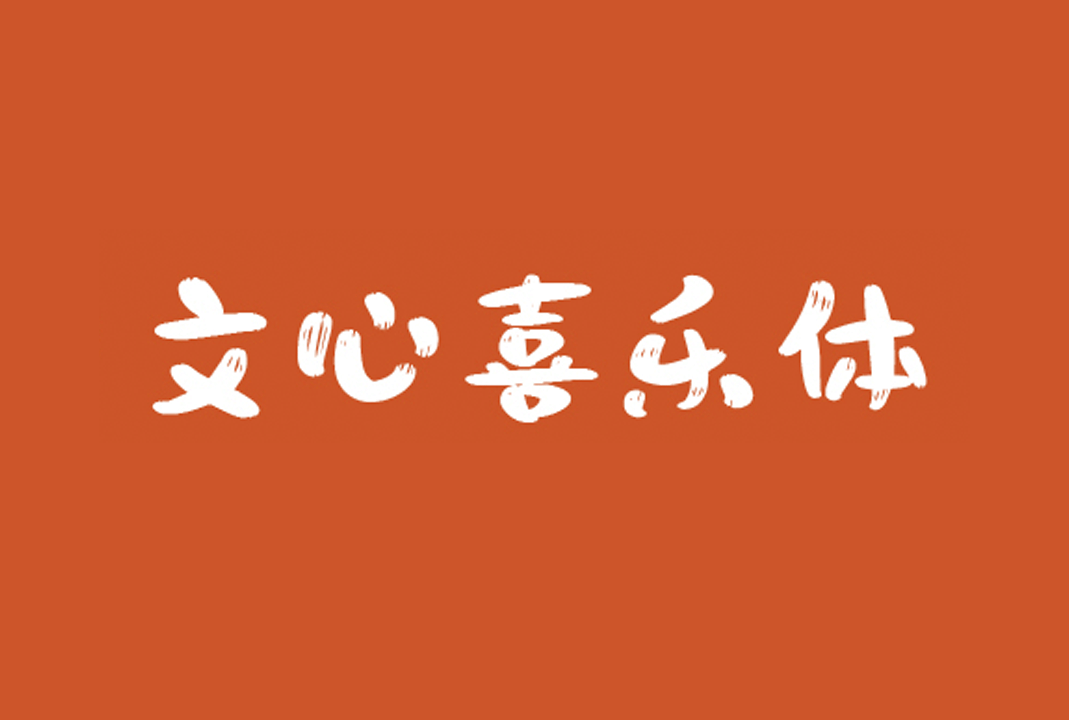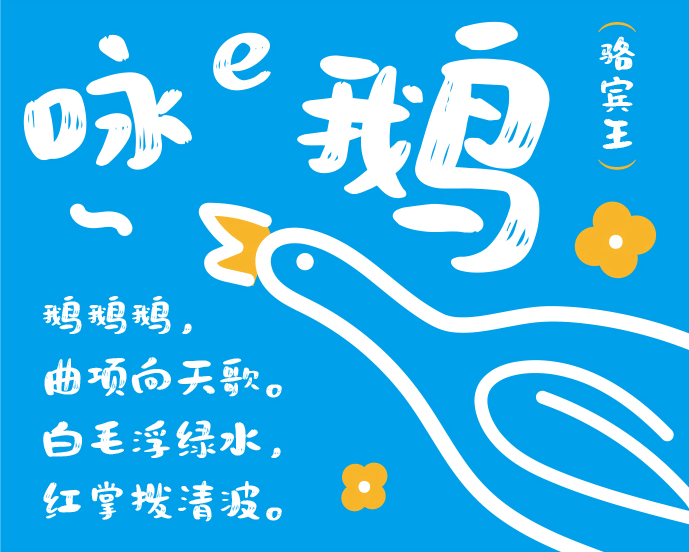
文心喜乐体(Wenxin Xile Font)是由网友发布的一款中文免费商用字体,该字体发布于古田路9号。
文心喜乐体(Wenxin Xile Font)是一款具有亲和力的字体,随性不拘谨的免费可商用字体。该字体字形饱满,笔画错落有致,横竖粗细、比例结构对比明显。作者在笔画中加入亮光纹理,增加字体的肌理质感与趣味性,富有活力,呈现出一种稚拙萌态。可做标题、正文,适用范围广泛。